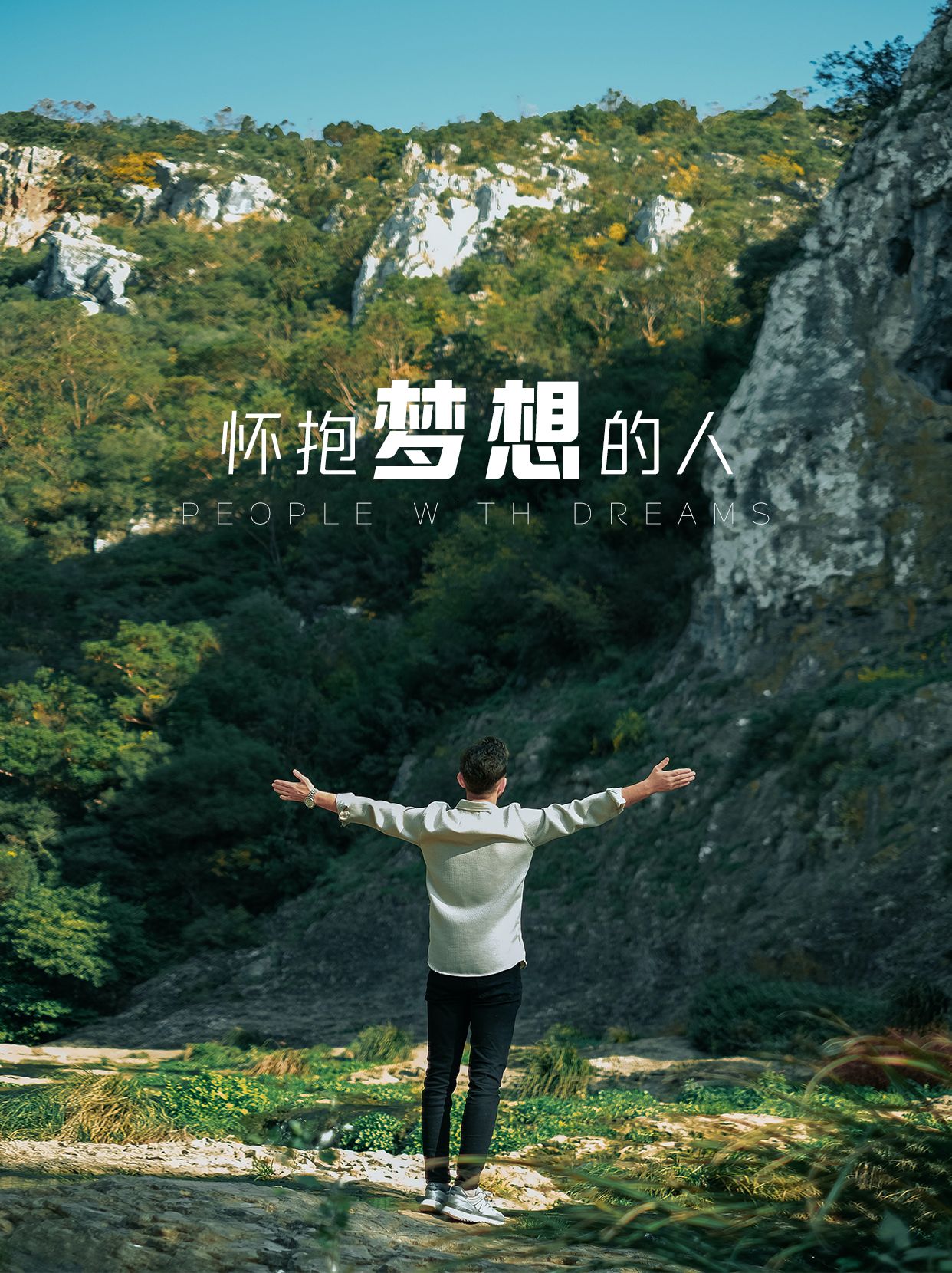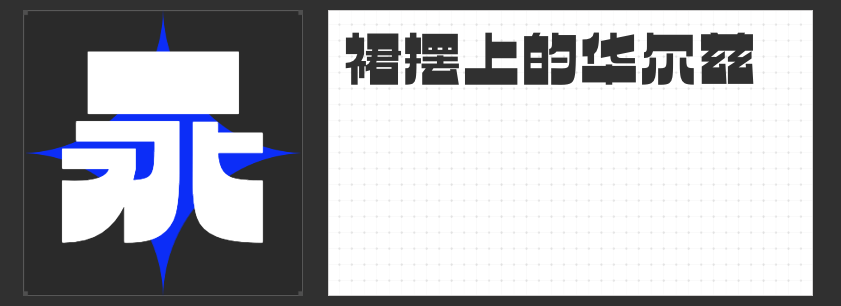
包装设计中的字库字体推荐:打造独特视觉体验
在包装设计中,字体选择至关重要。它不仅能传递产品信息,还能塑造品牌形象,提升产品吸引力。今天,为大家推荐三款适合包装设计的字库字体。
这款字体采用中西结合的设计手法,巧妙地将西文斜体装饰风格的浪漫优雅与汉字隶书笔画的韵味相结合。字体倾斜112度,赋予其独特的视觉动感。同时,通过汉字隶书笔画的撇、捺错落变化,在蚕头燕尾的韵味中构建出斜体字的韵律感和节奏感。这种微妙的平衡感,使得整体字体看起来轻松明快,既体现了字体的美感,又满足了包装设计中对视觉层次的需求。
2.励字造梦简 中粗
“励字造梦简 中粗”字体笔画圆融,没有尖锐的边角,给人一种温柔可爱的感觉。字体中多处使用圆弧转角,使得整体视觉效果圆润可爱,辨识度极高。这种字体适合用于儿童产品、食品包装等需要营造温馨、活泼氛围的场合。其萌动的字体形态能够迅速吸引目标消费者的注意力,提升产品的市场竞争力。
“励字逆反差圆舞简 超级黑”是一款字型方正、软硬兼备、笔画粗细对比明显的逆反差圆弧字体。该字体在逆反差直线版的基础上,将撇笔画、捺笔画、钩笔画和部分点笔画运用弧线处理,弧度饱满且富有张力。中宫较大,重心平稳,笔画对称,使得整体字体看起来既稳重又不失灵动。这款字体适合用于需要强调产品质感、彰显品牌个性的包装设计中。
综上所述,这三款字体各具特色,能够满足不同包装设计的需求。在选择字体时,建议根据产品特性和目标消费者群体进行综合考虑,选择最适合的字体来打造独特的视觉体验。